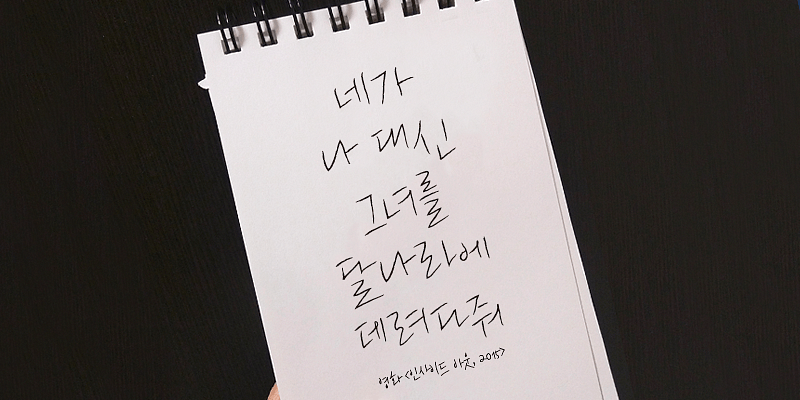
Sandoll GongbyunggakTab es una fuente manuscrita que permite disfrutar de sentimientos analógicos en el entorno digital.
El artista se ha centrado en acentuar la sensación de deslizamiento propia de las tabletas, dando un estilo de expresión analógico que se percibe desde las finas líneas adecuadas para escribir textos sentimentales.